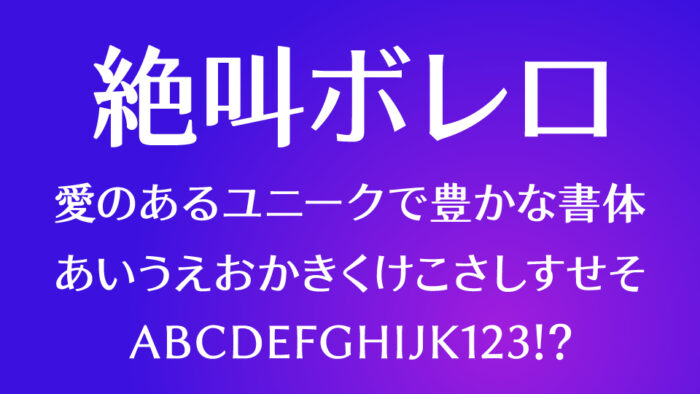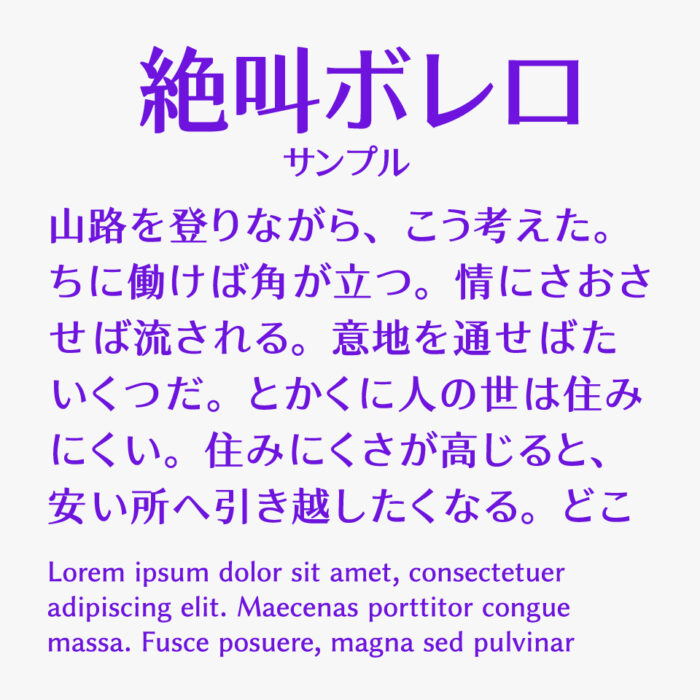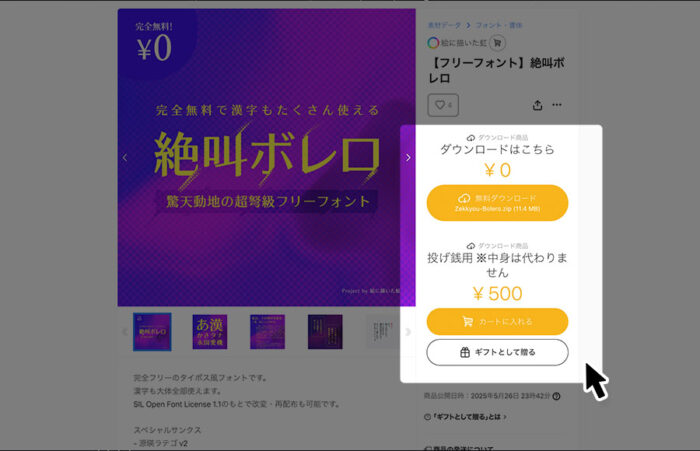
絶叫ボレロ
絶叫ボレロフォントは、漢字に「獅尾四季春加糖JP」フォントとひらがな・カタカナに「源暎ラテゴ」フォントが混植されたタイポス系フォントです。
2つのフォントが混植されていますが、一切違和感なく、かつどちらのフォントの整ったバランスながらもきちんと個性が際立っており、感情を揺さぶられるフォントです。
タイポス系はマンガの吹き出しやエピローグ部分に用いられることもあり、「絶叫ボレロ」フォントもマンガ用として作られています。